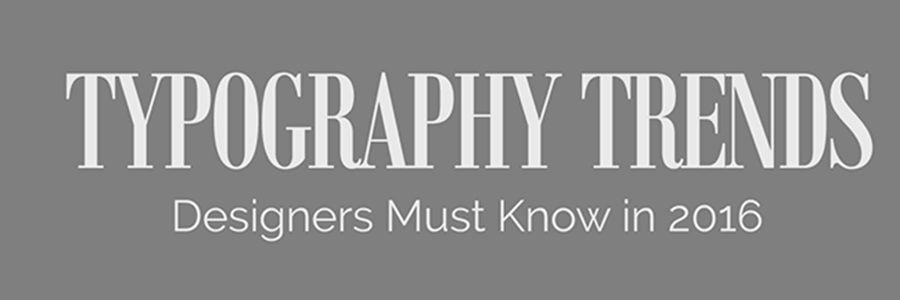
Quelles sont les grandes tendances de la typographie en 2016 ?
Quelles sont les grandes tendances de la typographie en 2016 ? Quelles seront les typos les plus populaires, leur format et leur utilisation ?
Le blog ThinkDesign partage une infographie très intéressante à ce sujet. On y retrouve également quelques suggestions de fonts, idéal pour renouveler un peu ses présentations. Voici les infos les plus intéressantes observées sur l’infographie :
• Les typos les plus populaires de 2016 sont : Oranienbaum, Cornerstone, Manifesto, et Stellar.
• Combiner la taille ou le style des typos est de plus en plus fréquent
• Conseil : pour les typos “responsives”, il convient de faire des titres eux aussi « responsives » et d’ajuster le texte en conséquent
• Les typos à la mode et web friendly : Ubuntu, Arvo, Oxygen, Signika, Oswald, Pacifico…
• Cette année les empattements (Serif) reviennent à la mode